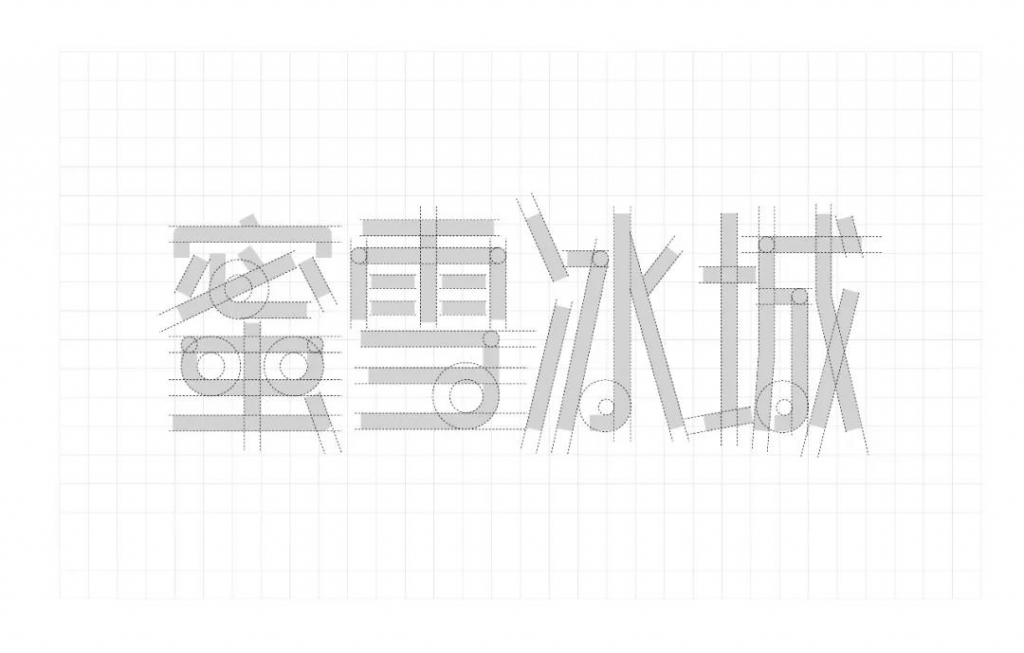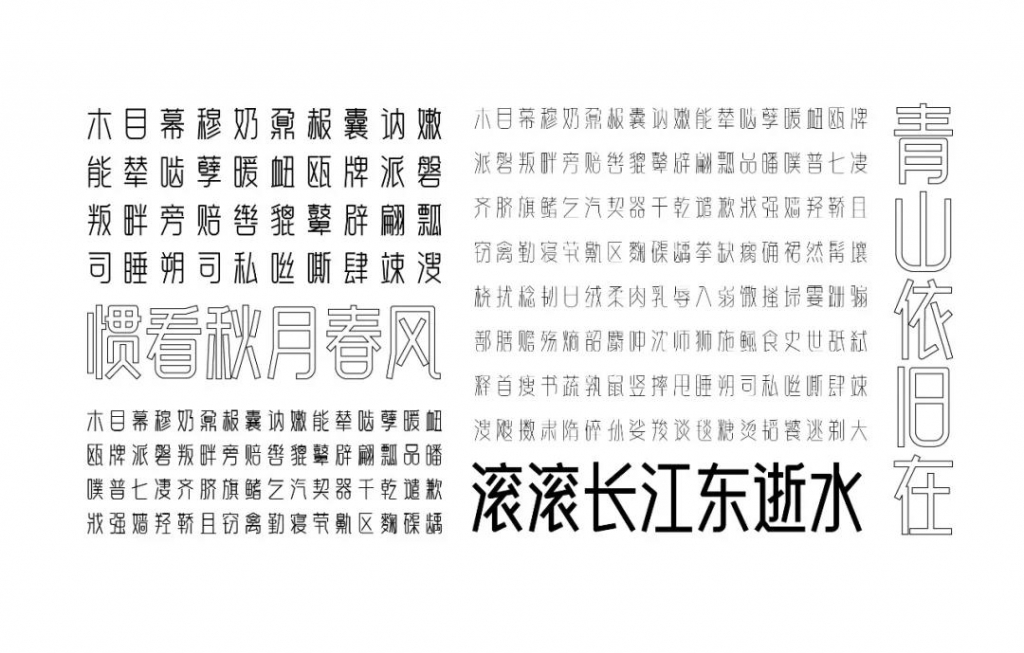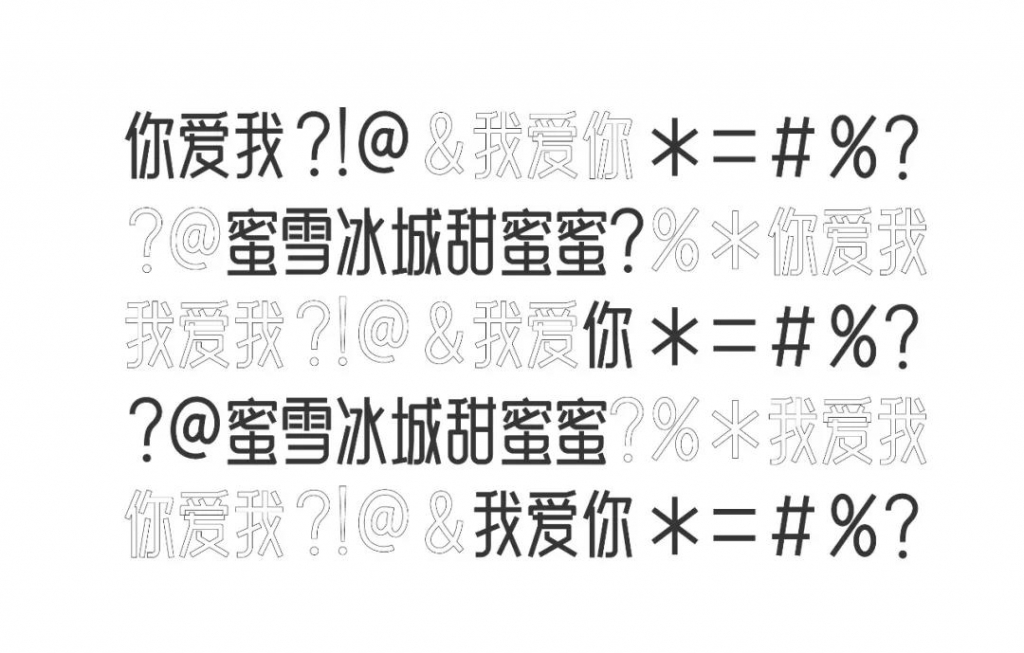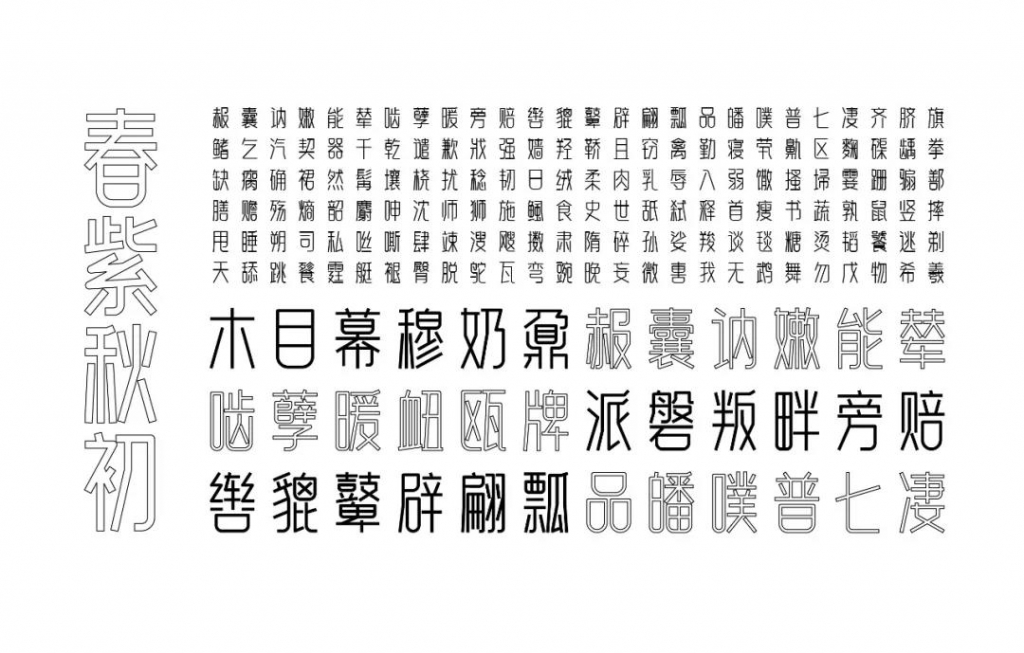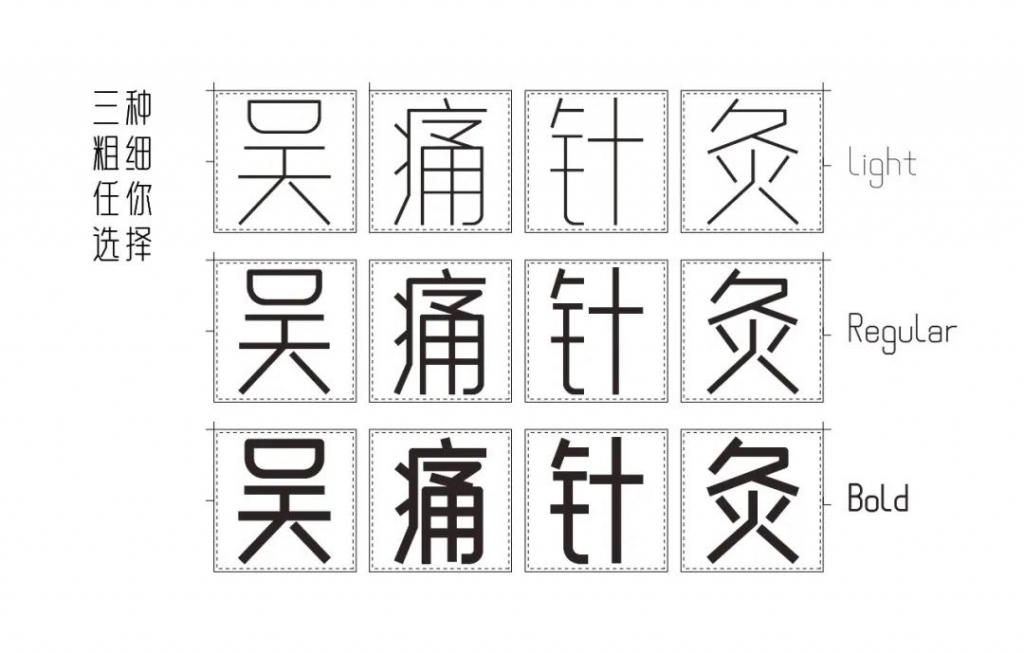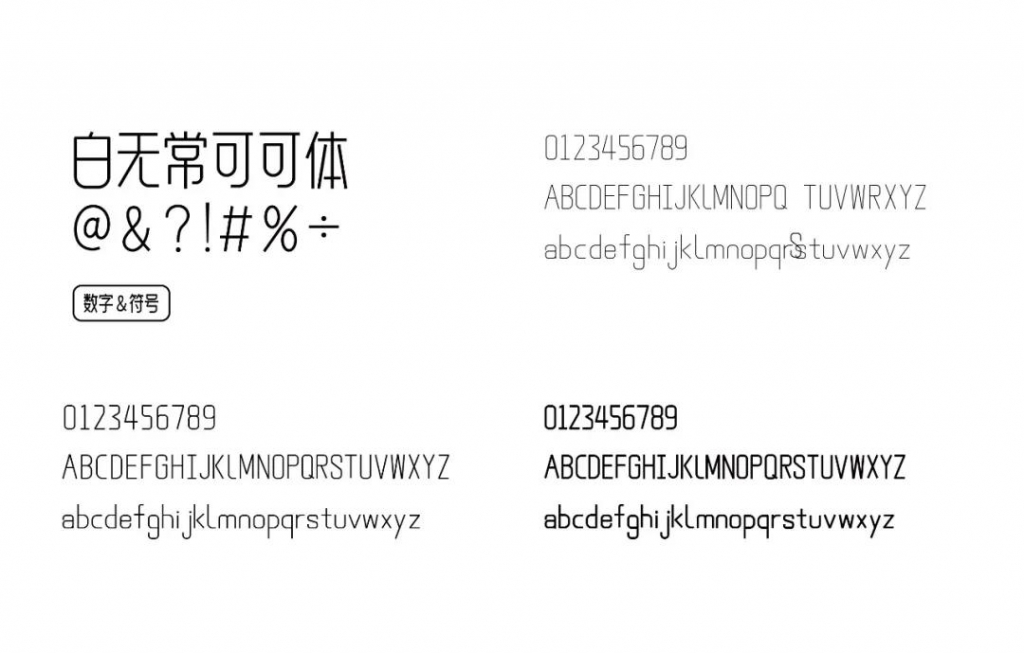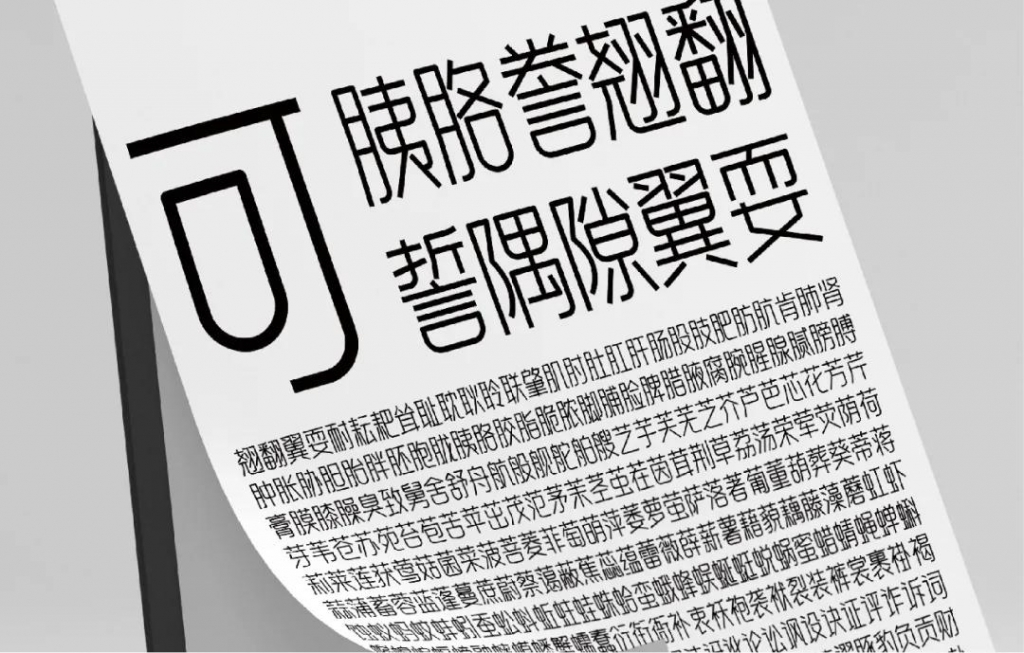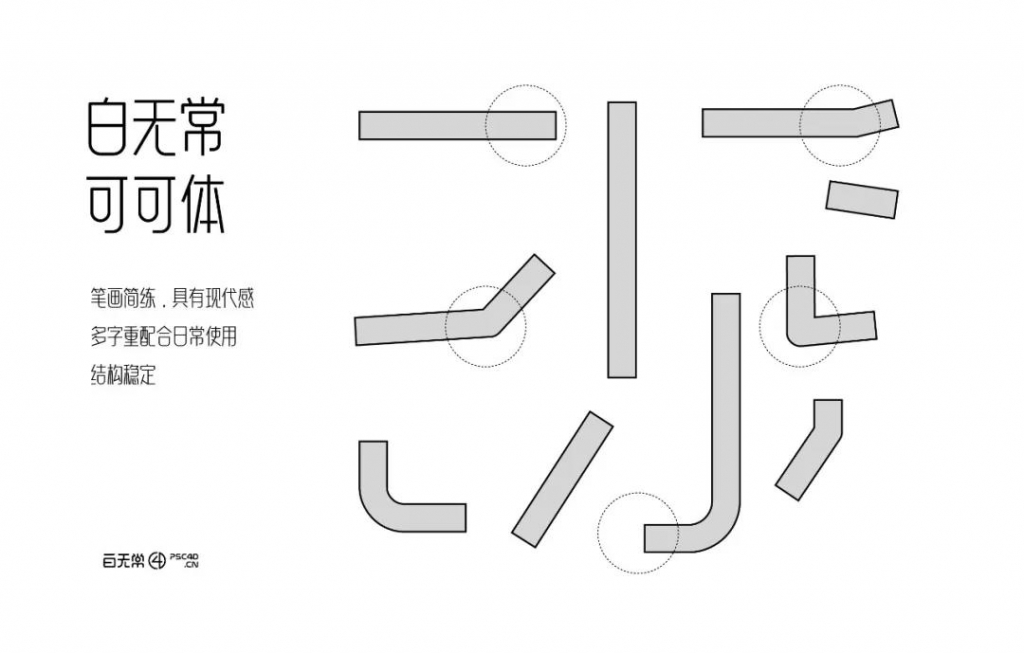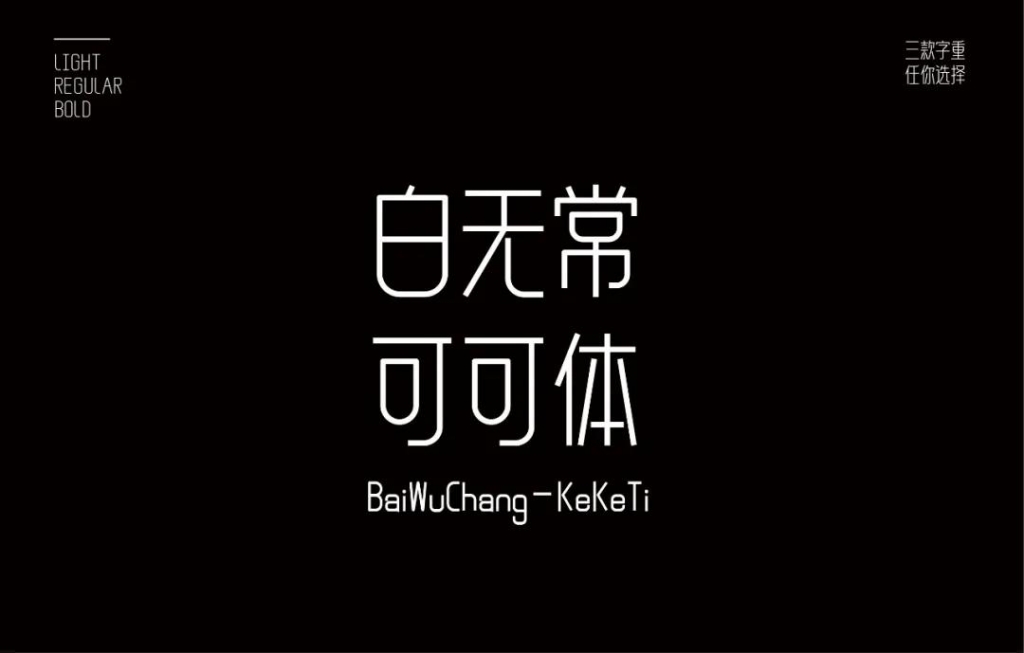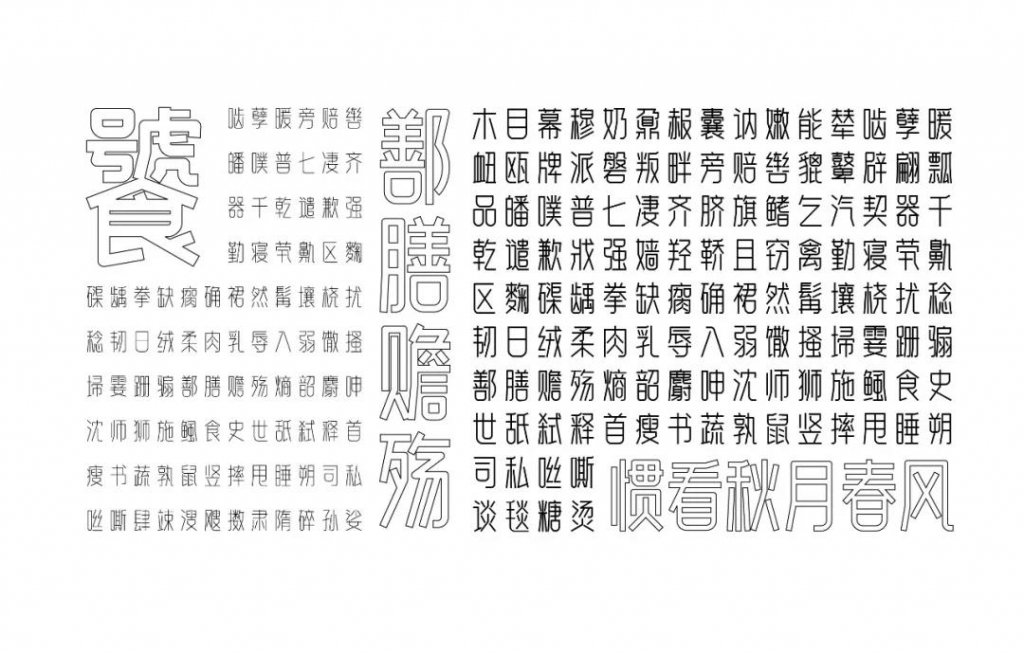
去年的时候就思考一个问题,好像每个设计作品都有它的生命周期,特别是电商这块。基本上线个几周就下线了,有些就几个小时。好像设计作品的生命的周期特别短,价值也不是特别大。 就想着做字体,这个事情和发发讲了下,然后发发就离开了我们去了字节跳动,浪费人才在我这里两年既然没有让他做个字库。
这款字库是我去年拜托刘兵克老师工作室制作的,一开始就想做一个好细好细的字体,连名字的想好了,白无常好细哦字体。然后兵哥告诉我,给我做了三个字重,所以不能说好细字体。非常非常感谢兵哥,给我打过折,还额外多做了二个字重!
所以就换了个名字,选了一个我女儿的名字的可字,所以就叫白无常可可体,嘿嘿~~
“白无常可可体常规”是一款书写很新颖的字体,字体大方,适合各种设计作品使用!欢迎下载!